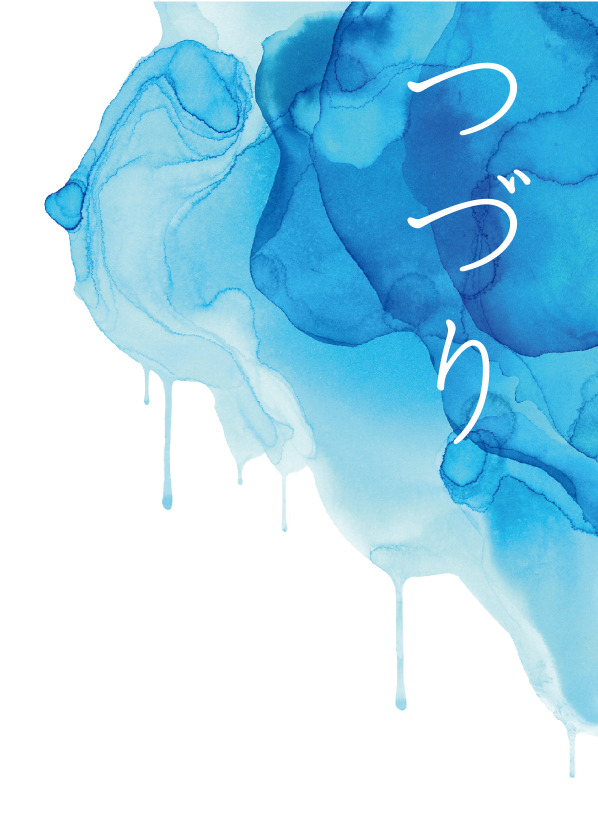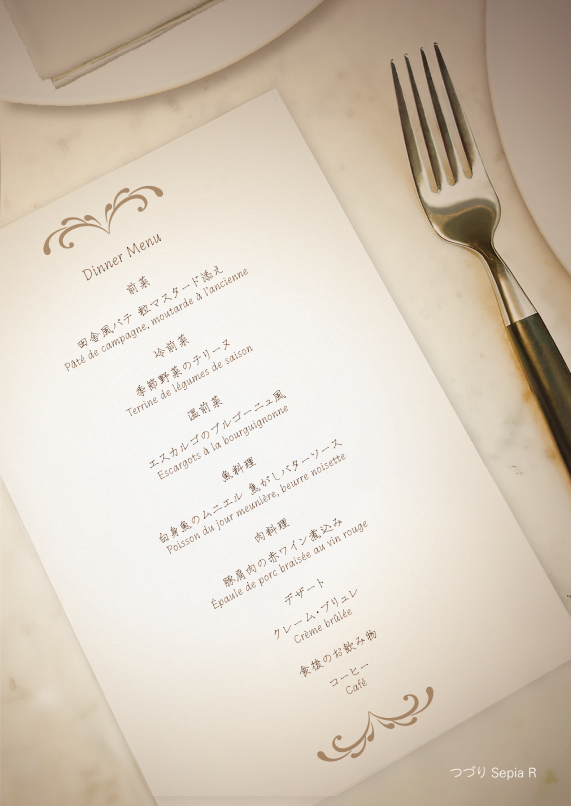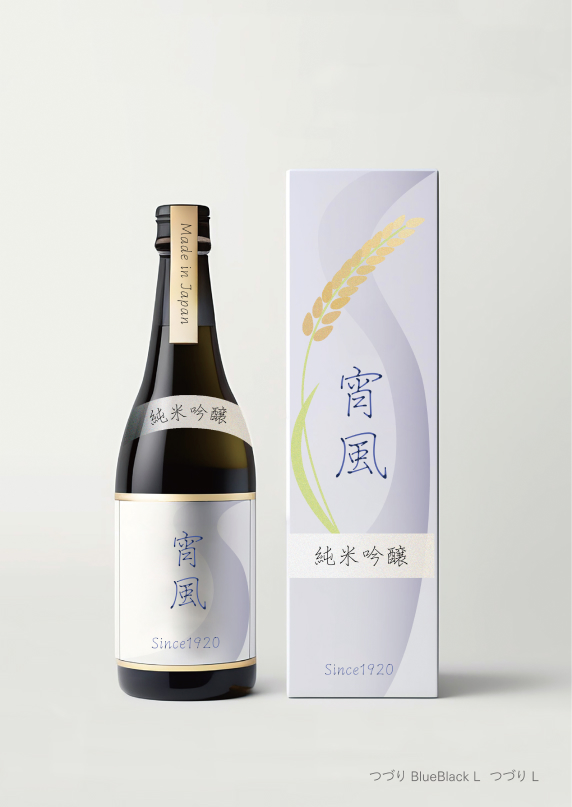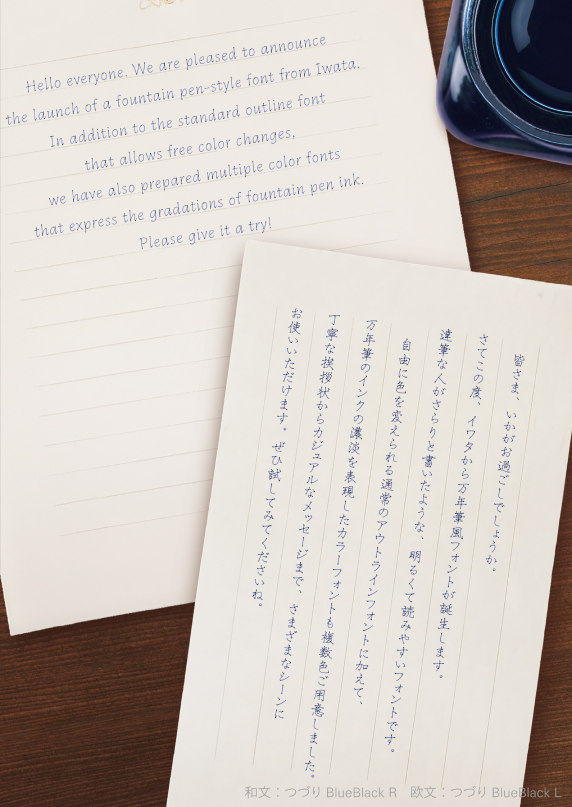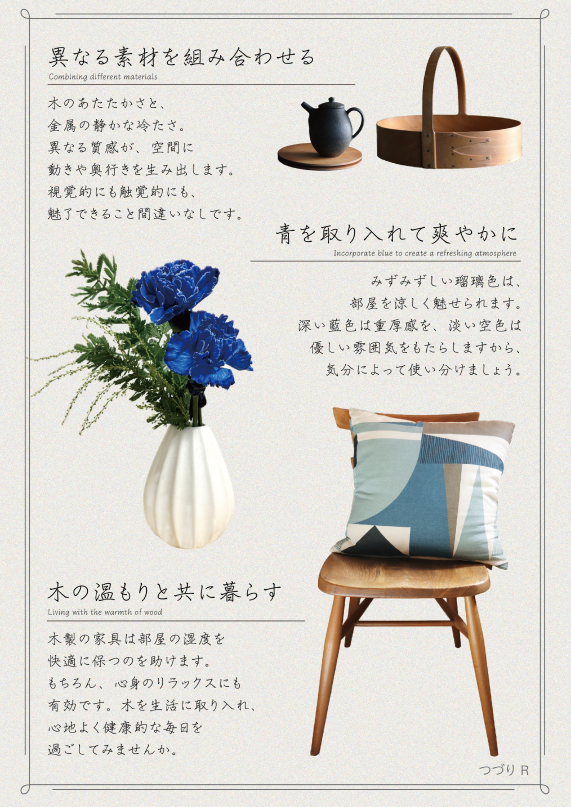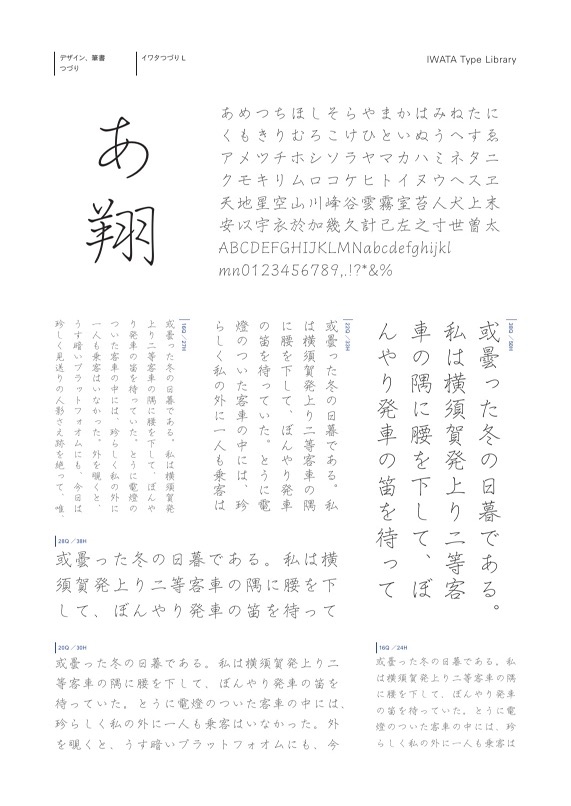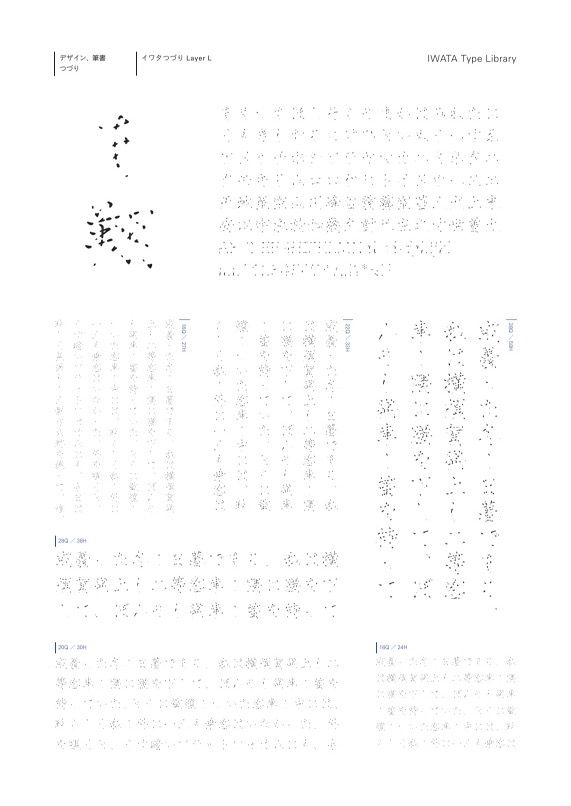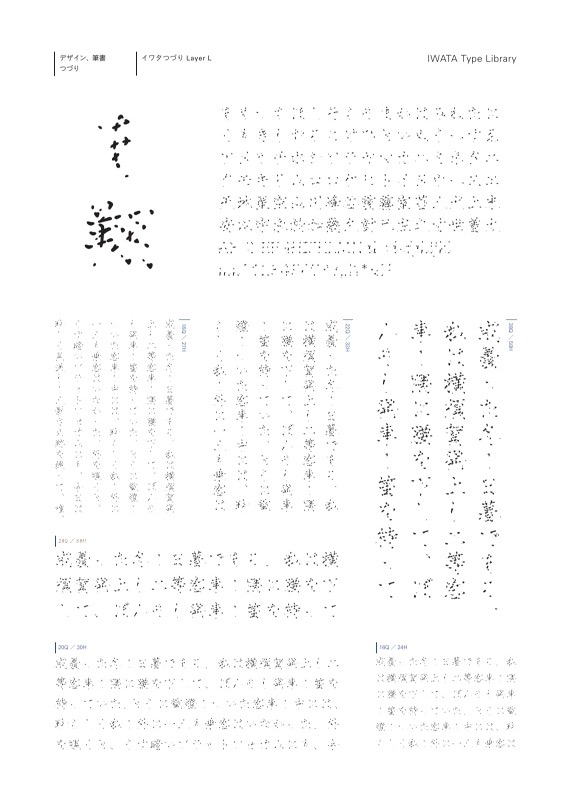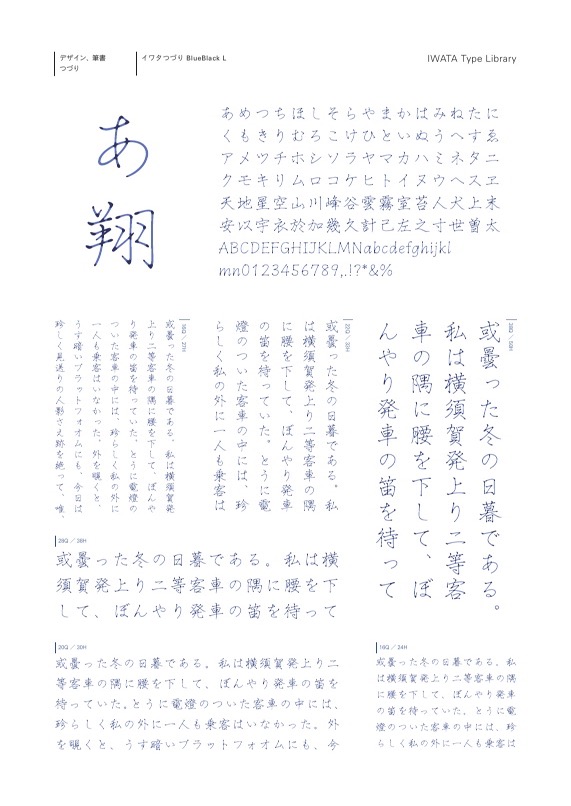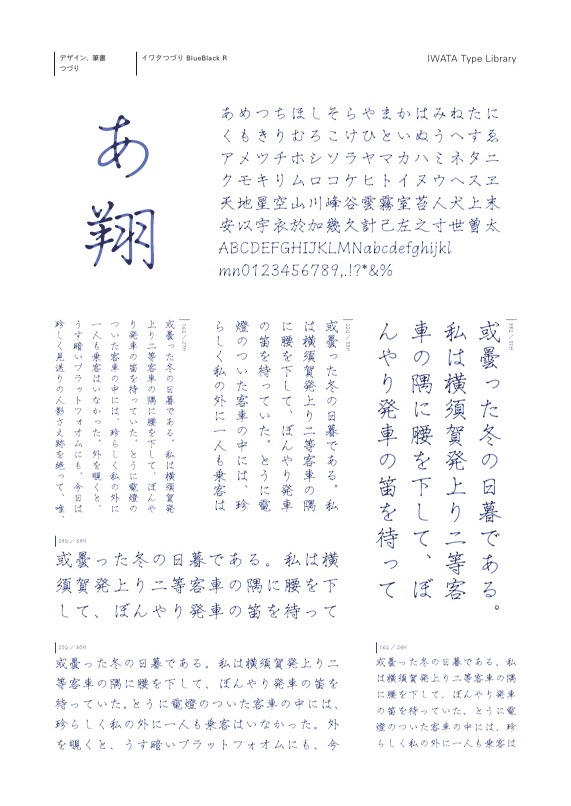
つづり
特徴 Concept
美の書き比べ
書体の特徴
エレメント骨格
美文字なフォントイワタつづり
Layerフォントの使い方
LightやRegularとLayerを重ねることで、
万年筆風の色合いをお好みのカラーで簡単にお楽しみいただけます。
〈例1 明るい背景色での使い方〉
例1: LightとLayer Lを重ねた愛の文字
〈例2 暗い背景色での使い方〉
例2: RegularとLayer Rを重ねた詩の文字
使用例 Usage Examples
使用例1
使用例2
使用例3
使用例4
使用例5
組見本:イワタつづり Light
組見本:イワタつづり Regular
組見本:イワタつづりLayer Light
組見本:イワタつづりLayer Regular
組見本:イワタつづりBlueBlack Light
組見本:イワタつづりBlueBlack Regular
組見本:イワタつづりSepia Light
組見本:イワタつづりSepia Regular
組見本:イワタつづりWhite Light
組見本:イワタつづりWhite Regular